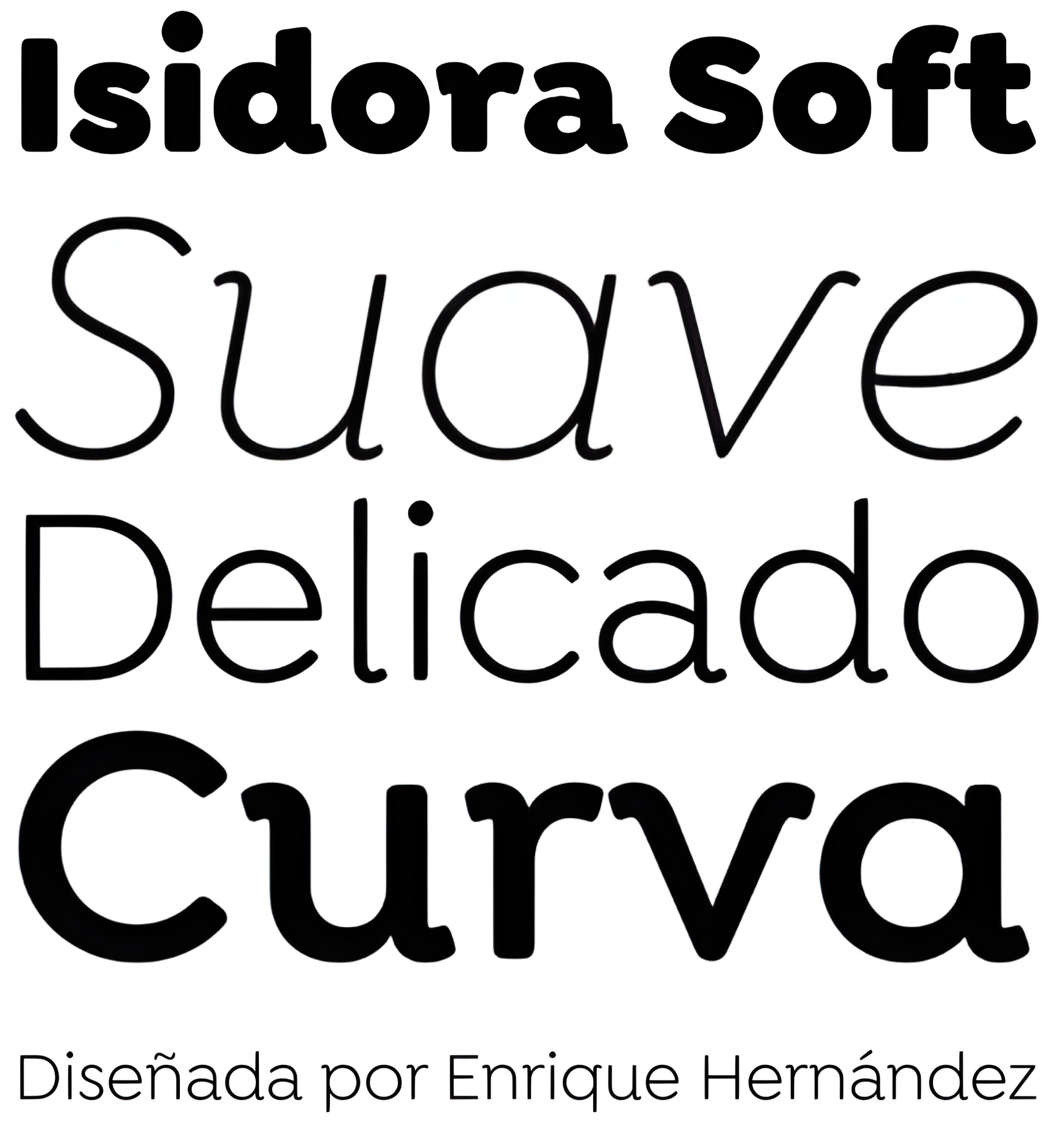
| Año | 2019 |
| Créditos | Enrique Hernández |
| Descripción | Isidora Soft es la nueva versión de Isidora - una Bestseller de MyFonts en 2016. Su redondez, terminaciones suaves da una apariencia amigable y expresiva, y su estilo moderno y contemporáneo, una altura X pequeña y proporciones clásicas la hacen una excelente elección para titulares, logotipos, branding, libros, revistas, motion graphic, y para el uso en web y TV. Isidora Soft consiste de dos versiones de 7 pesos: una regular y otra alternativa, la cual es más expresiva y juguetona comparada a su contraparte. Ambas versiones incluyen itálicas a juego, resultando en un total de 28 estilos. Isidora Soft contiene un set de 452 caracteres que soportan más de 200 lenguajes derivados del latín. |
| Familia(s) | Thin, Thin It, Light, Light It, Regular, Regular It, Medium, Medium It, Semi Bold, Semi Bold It, Bold, Bold It, Black, Black It, Alt Thin, Alt Thin It, Alt Regular, Alt Regular It, Alt Medium, Alt Medium It, Alt Semi Bold, Alt Semi Bold It, Alt Bold, Alt Bold It, Alt Black, Alt Black It |
| Estilos | 28 |